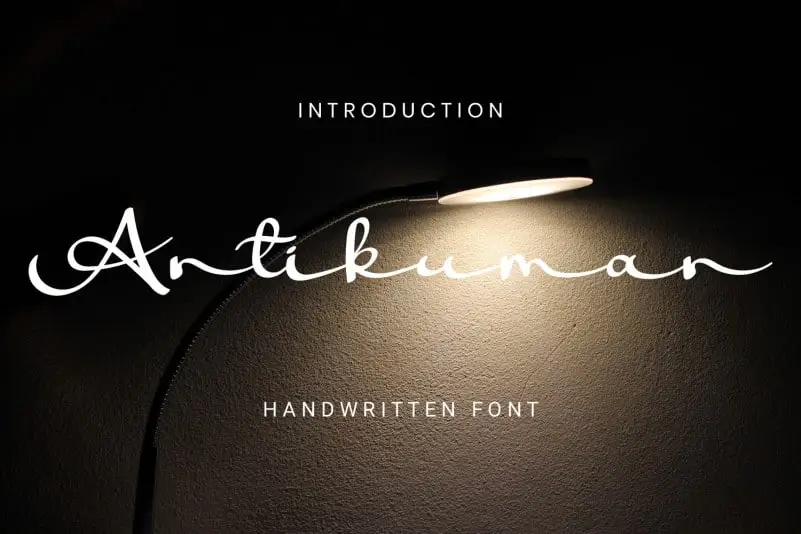
Antikuman Handwritten Font – Download Grátis
Antikuman Handwritten Font é uma fonte de escrita manuscrita que flui suavemente, caracterizada por seu toque elegante. Perfeita para seus projetos favoritos, essa fonte apresenta um estilo distintivo e eterno que se destaca na cena dos materiais gráficos digitais. Recomendada pelos amantes da escrita manuscrita e desenhadores de layout, Antikuman é a escolha ideal para criar designs impressionantes e únicos. Não perca a oportunidade de dar um toque especial ao seu próximo projeto com essa fonte encantadora e única.